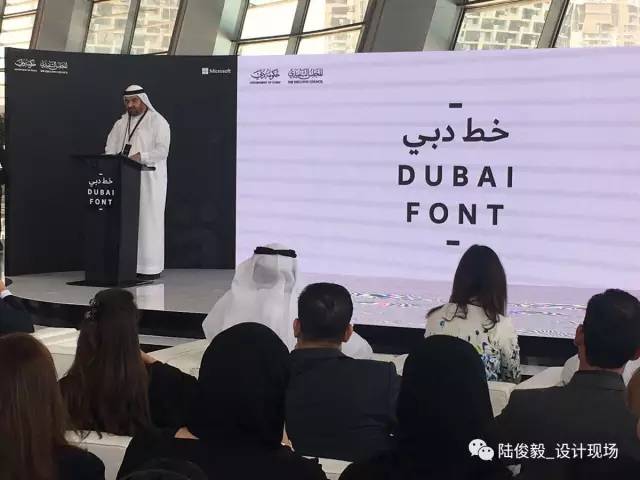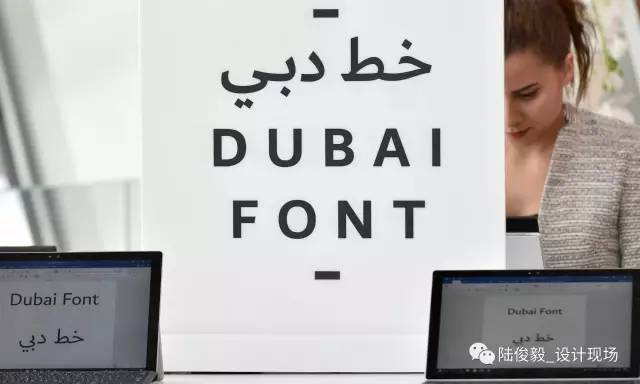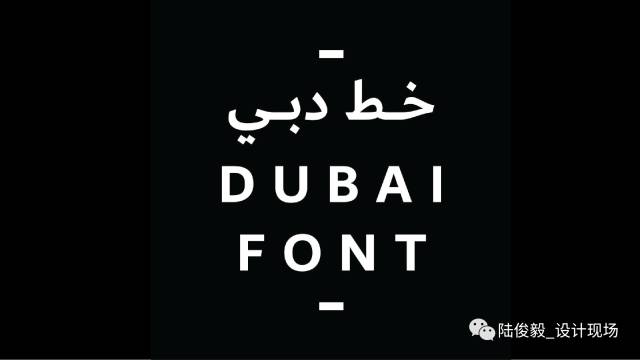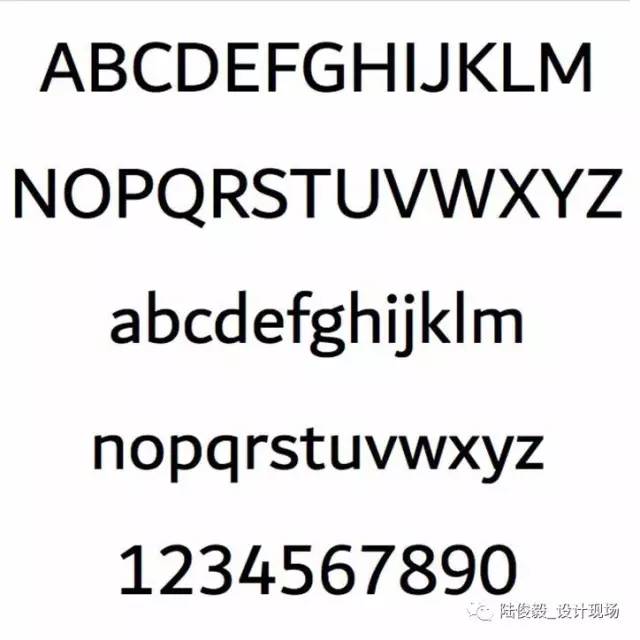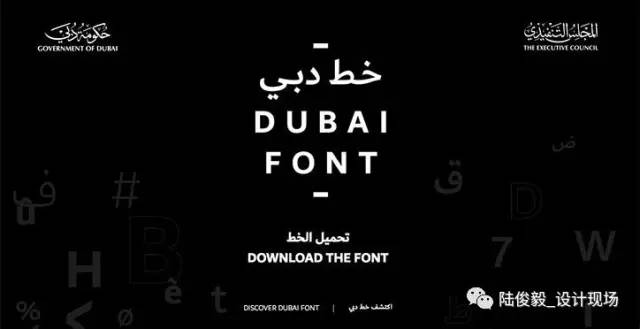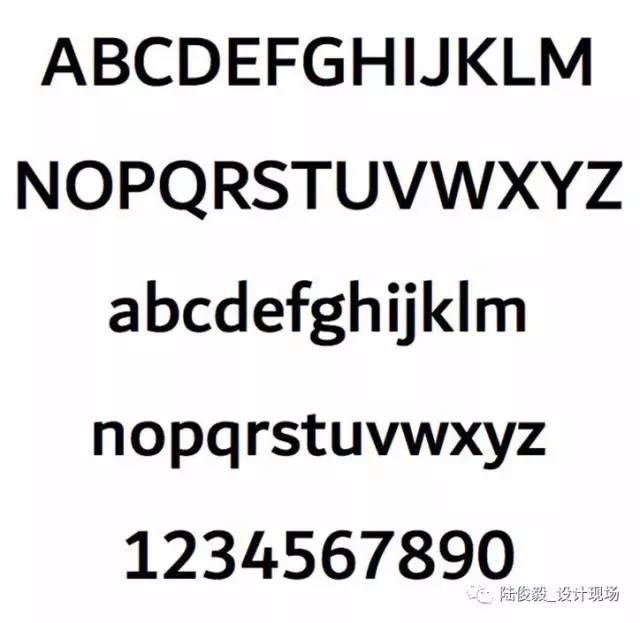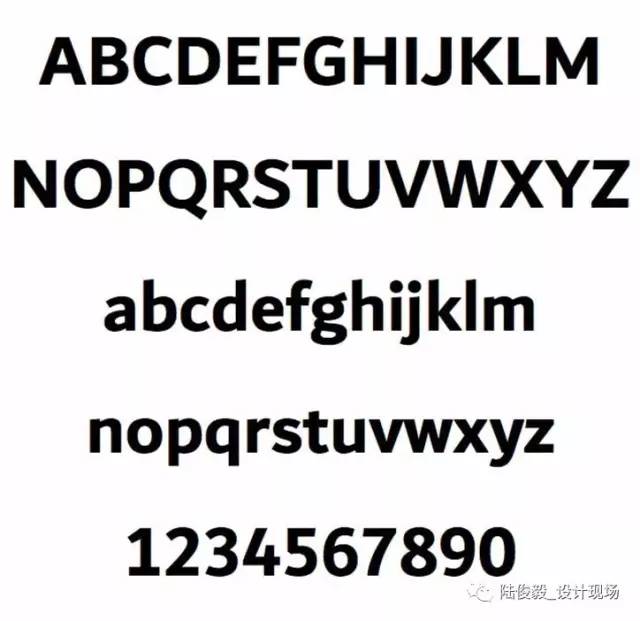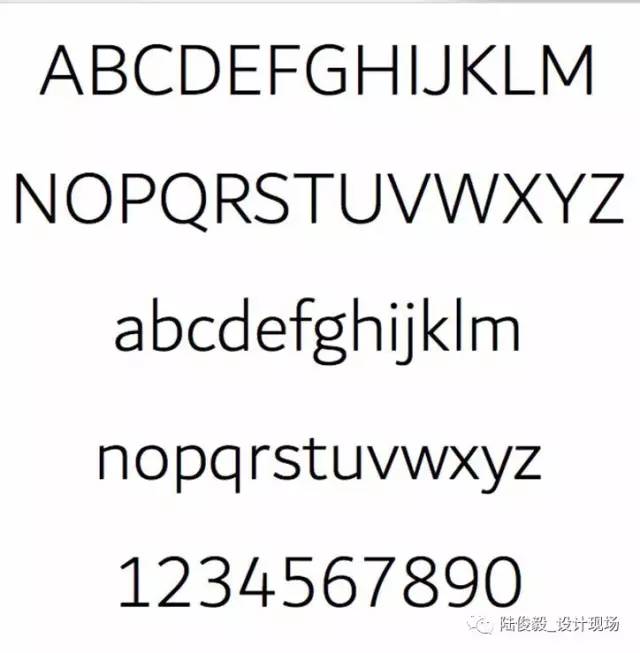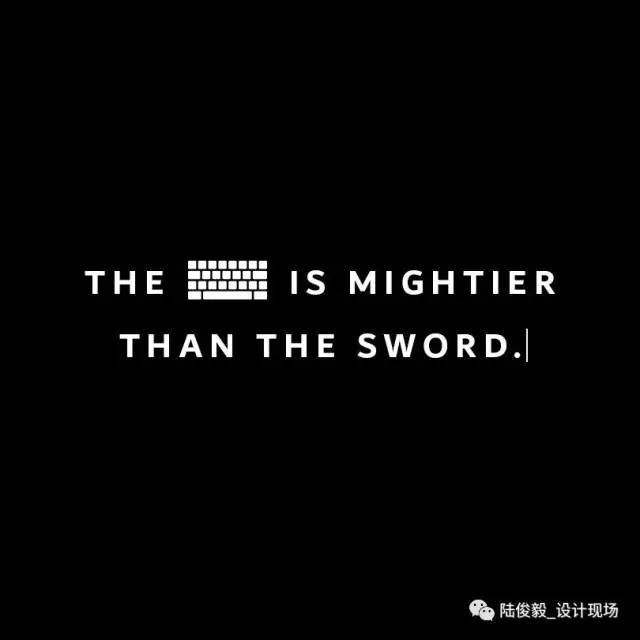
微软为迪拜设计专属“Dubai”字体,23语言适用。
说起迪拜,第一印象估计就是“奢华”、“土豪”,迪拜拥有世界第一高楼哈利法塔和全球唯一的八星级皇宫酒店,这座城市仿佛要把一切都变得极尽豪华。
但迪拜最近做的一件事看起来与其向来的华丽形象有点格格不入,近日迪拜与微软合作,推出一款名为“Dubai Font”的专属字体,迪拜也成为全球首个拥有微软专属字体的城市。
几十年来,将阿拉伯文转换成数字印刷体对设计师一直是个挑战,难度在于将优雅的书写体转变为基于像素的数字格式,并确保它们在各种媒介上(印刷品、网站、视频和手机)都是清晰可读的。
据悉,这款专属字体是迪拜王储哈姆丹委托微软共同设计的,旨在“给世界提供一个新的沟通工具,用表达的力量团结全世界。”
很少有设计师能做到功能和美观的平衡,从这个意义上来说,Dubai 字体的创始人 Nadine Chahine 做得不错。Chahine在接受采访时说,自己的目标就是让字体变得清晰,同时将迪拜这座城市的精神,传达给带着开放精神的其它文化。
“Dubai Font”具有拉丁语和阿拉伯语两个版本,适用于23 种语言,包括细体、常规、半粗体和粗体四种字重,同时也提供了适用于 Windows、Android、Mac OS 的 OpenType TTF 字体格式和适用于 Adobe 的 OpenType CFF 的字体格式,以及 Web 的专用字体格式,供微软全球 1 亿 Office 365 的用户免费使用。
Monotype/Microsoft/The Executive Council of Dubai: Dubai font
Monotype/Microsoft/The Executive Council of Dubai: Dubai Regular
Monotype/Microsoft/The Executive Council of Dubai: Dubai Bold
Monotype/Microsoft/The Executive Council of Dubai: Dubai Light
Monotype/Microsoft/The Executive Council of Dubai: Dubai Medium
(Dubai Font 不同字重的表现)
这款字体还有一个重要的意义,就是弥补了阿拉伯语和拉丁语的字体设计差距。前段时间 Google 和 Adobe 发布的思源宋体就解决了在东亚地区统一字体的使用问题,为中文互联网带来了更为丰富的视觉体验。
尽管Dubai字体没有最高建筑或高速列车那么宏大,不过迪拜王储哈姆丹已经连续在推特上发布了好几条关于这款字体的消息,他还要求所有政府机构必须在正式通信中使用这款字体。
4月30日,王储发布了一条推特为这款字体背书,称它为“反映阿联酋文化遗产的独特项目”,赋予它“与全世界接轨”的任务,并且会在每一条推特后面加上 #ExpressYou标签。
王储还推出了一则关于Dubai字体的视频,其中提到:“表达方式没有界限,没有限制”,“表达是力量和自由”,“它定义你是谁。现在你有了一种新的方式表达自我,信仰以及人生经历。”
从迪拜这次的专属字体来看,城市专属字体固然带着城市宣传的目的,但如果其字体设计能优化我们在不同设备的阅读体验,为这个庞大的互联网世界增添一种新的表达方式,这样的城市名片在这个数字时代,可能会比一栋耗费巨资的“地标”影响更为深远。